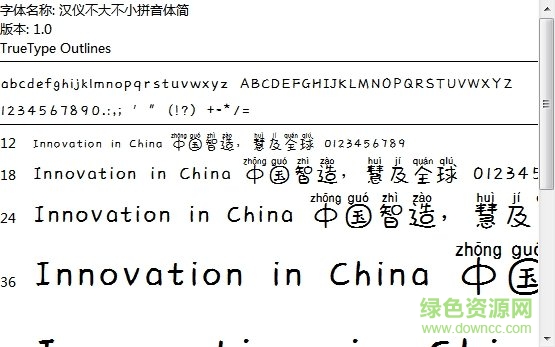
漢儀不大不小拼音字體
漢儀不大不小拼音體是一款迥異與漢儀拼音字體卡通字體,中英文都有著較為可愛Q夢的兒童字體造型,中文漢字上還有這非常準(zhǔn)確的拼音標(biāo)注,讓文字更加顯眼生動,綠色資源網(wǎng)今日推薦!
漢儀不大不小拼音字體特色
漢儀不大不小拼音體,拼音字體界的一股清流,字體大小舒適,筆畫粗細(xì)均勻,拼音與字緊疏有序。有關(guān)字體方面的問題,或者有喜歡的明星。